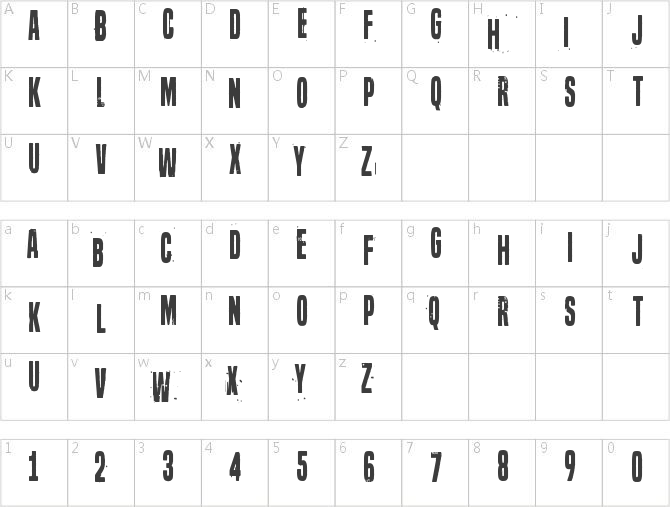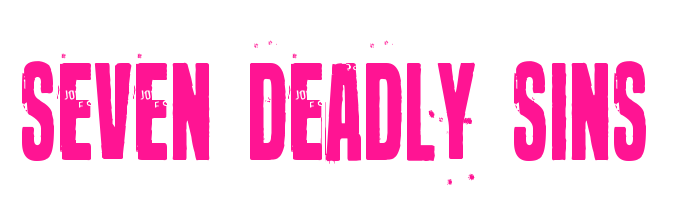
Seven deadly sins 詳情頁
Seven deadly sins
Seven deadly sins字體字庫是一款讓人賞心悅目、百看不厭的英文字體,適合各類廣告和產(chǎn)品包裝設(shè)計應(yīng)用,字體大小0.06MB,格式為ttf字體,上傳用戶是錦程正陽,作者/版權(quán)方為未知